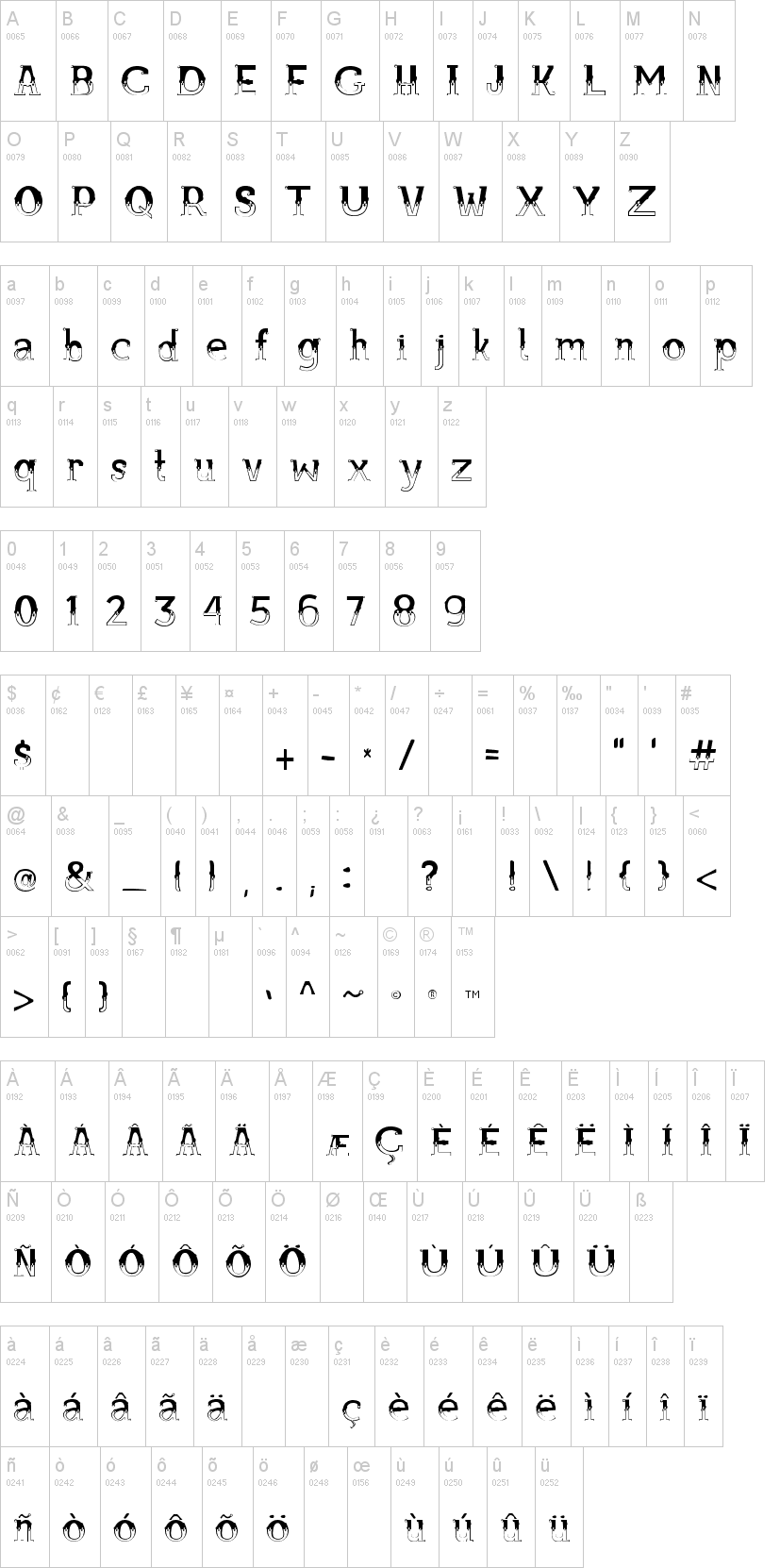
Шрифт Bule
A Bule é uma fonte criada a partir de uma seleção de imagens do universo do café, utilizados no processo de preparação do café até a sua conservação como exemplo, grãos, cafeteiras, colheres, moedores, bules e garrafas térmicas.
Foi projetada para ser uma tipografia display. O desenho se destaca mais pela contra forma do que a própria forma em si, principalmente pelas hastes e barras vazadas. Alem disso o desenho também reflete a uma linguagem retro e teve como inspiração alguns cartazes pin-up.